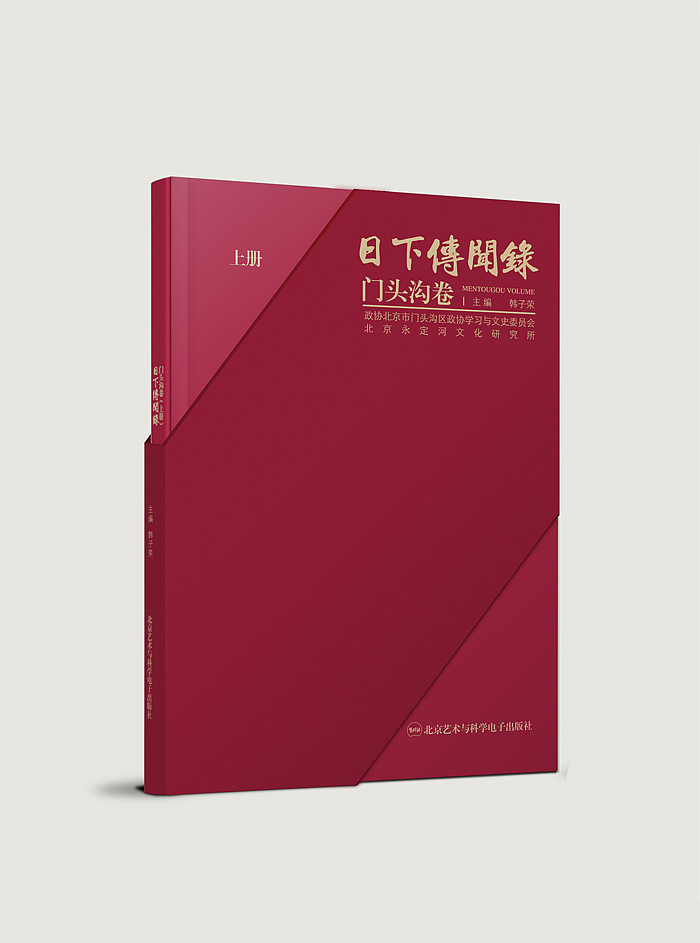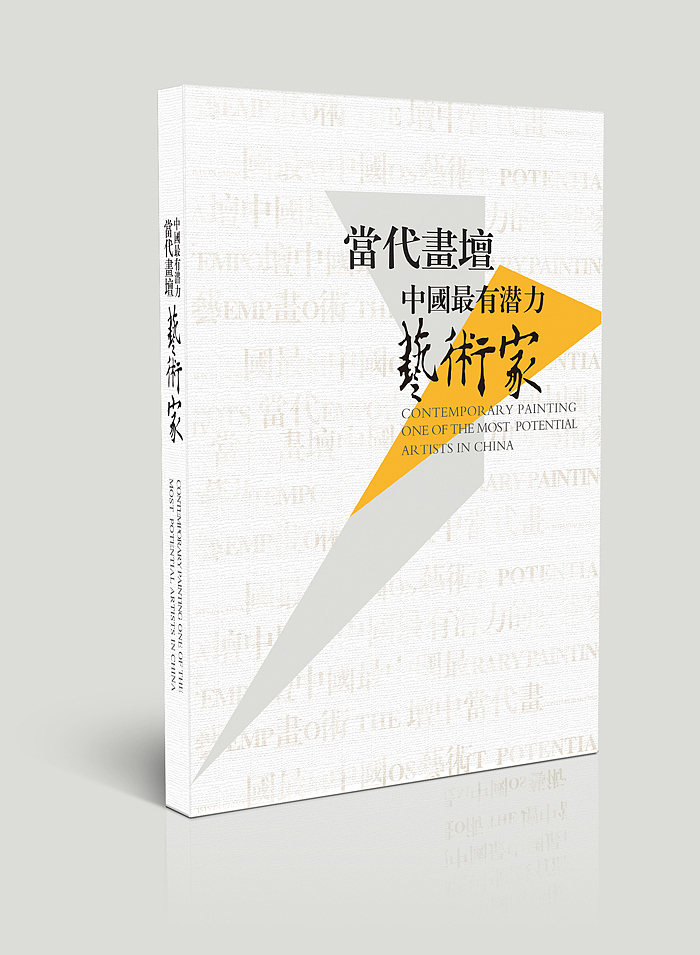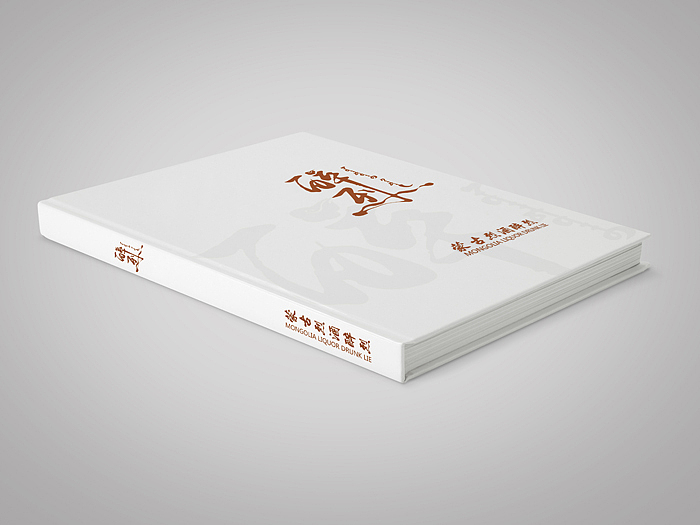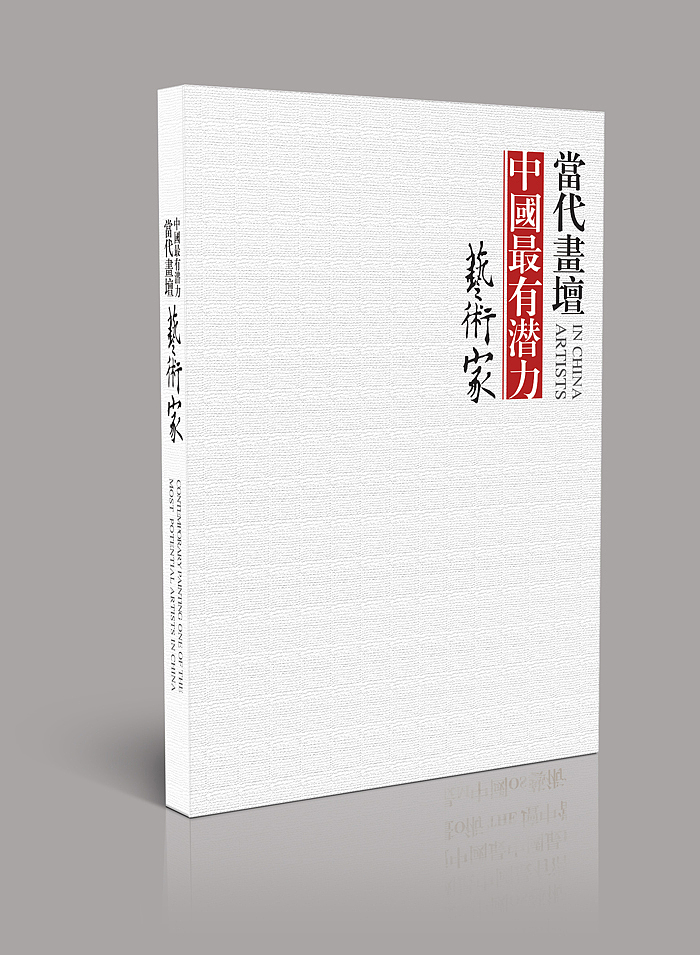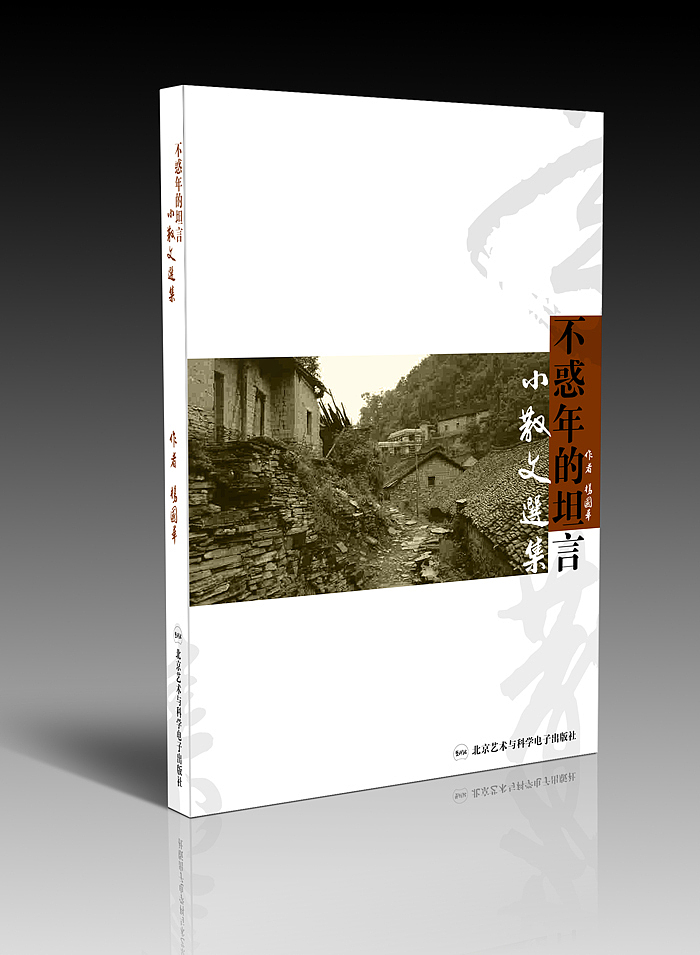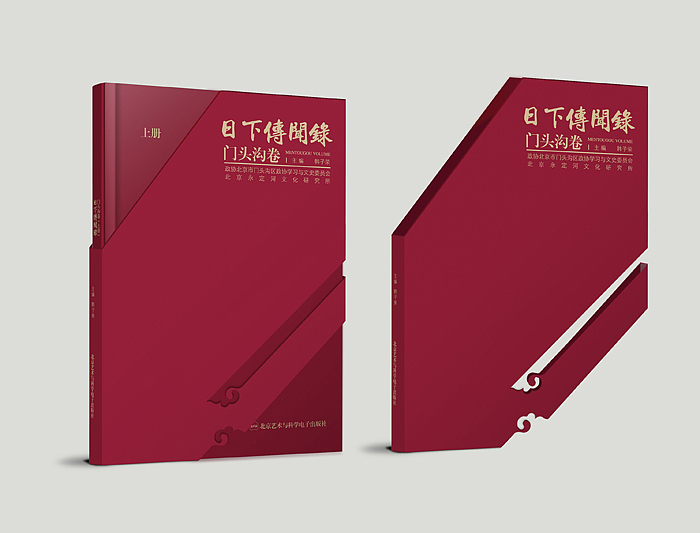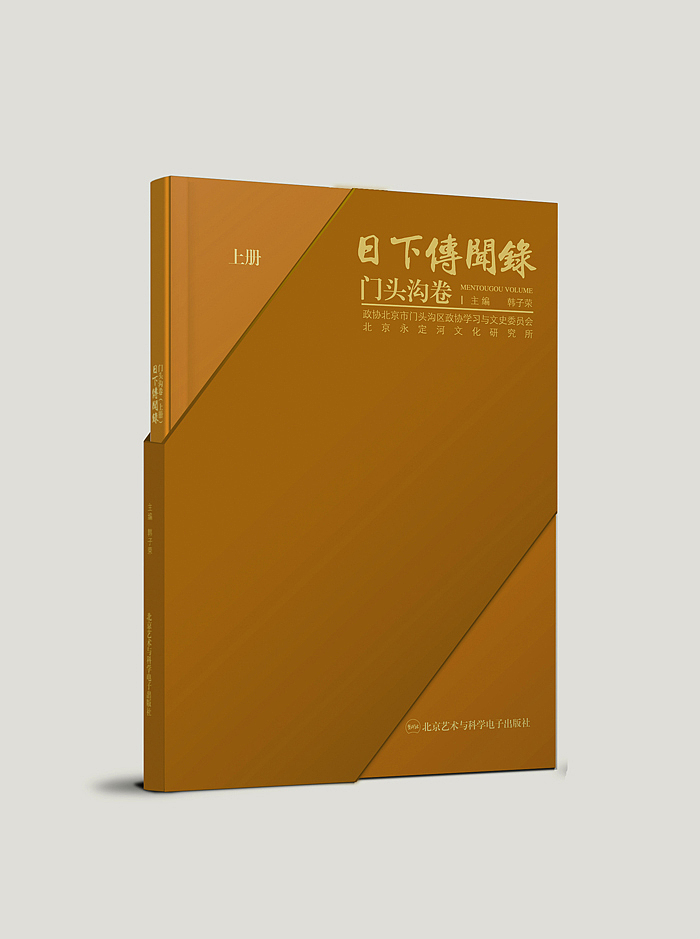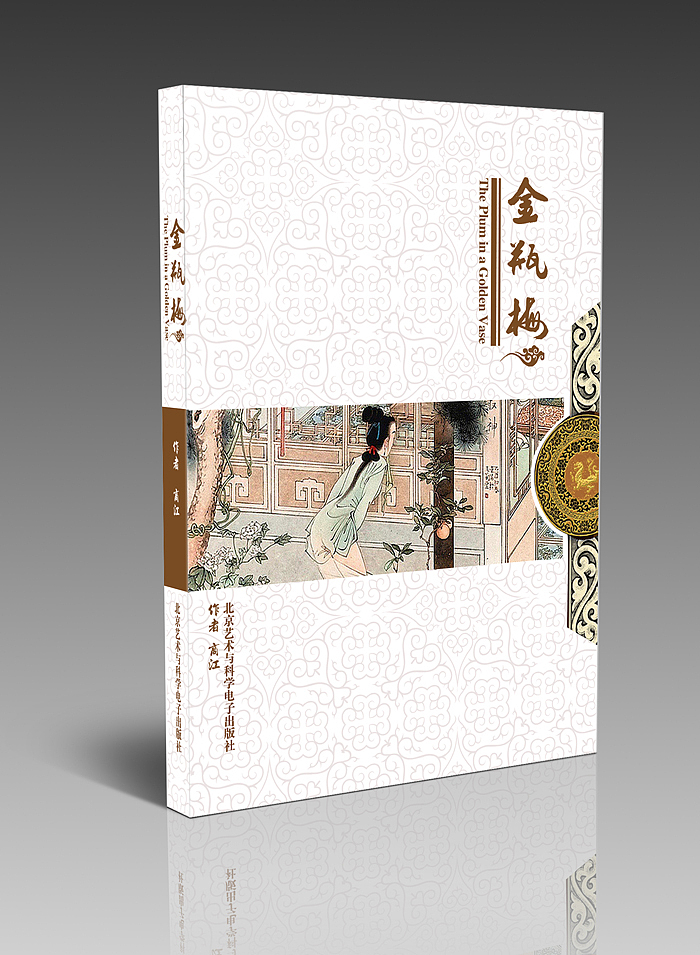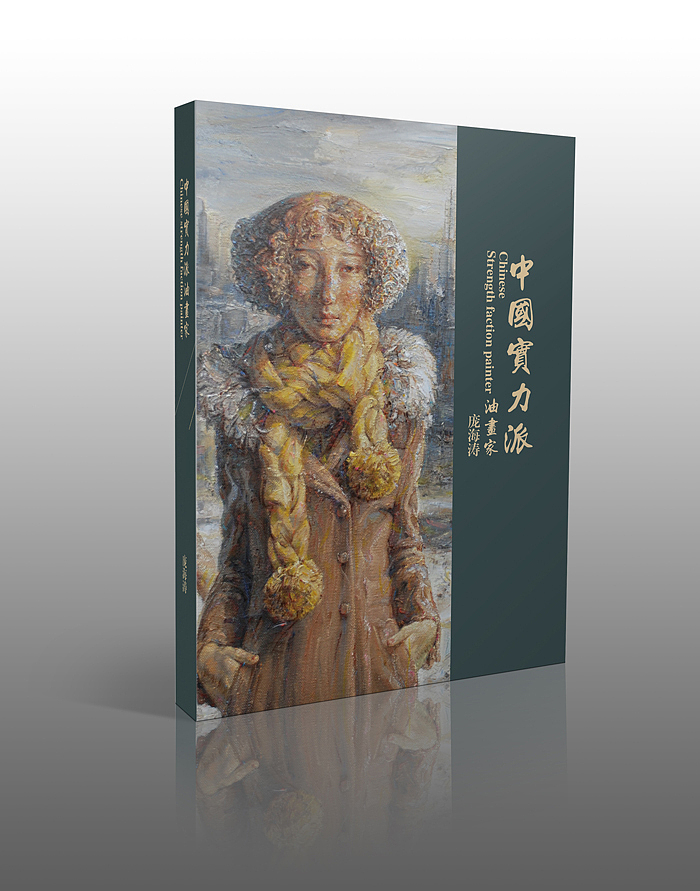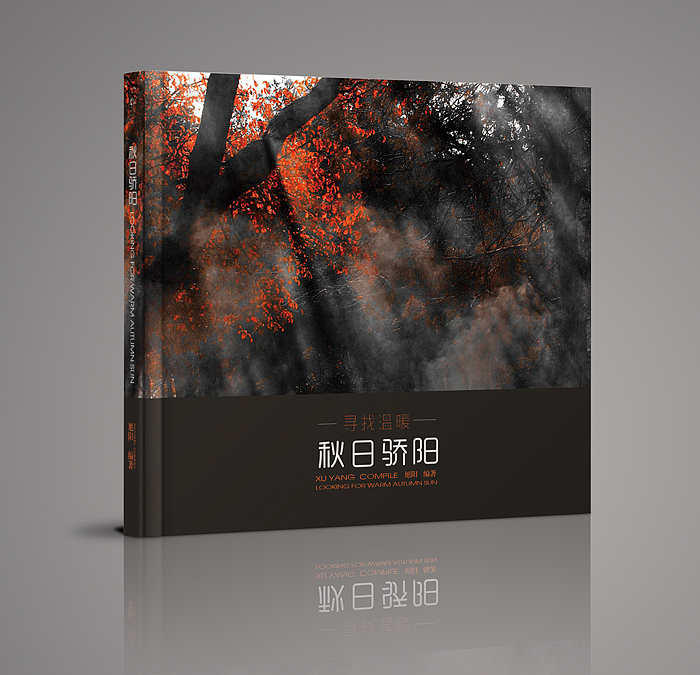
精装书籍封面和字体设计
自己一向喜欢古典的书籍,从小就喜欢写毛笔字书法和钢笔字,随着现代化的冲击,自己的毛笔也丢弃了很多年。但是这些文化类的书籍自己还是很大的感觉和兴趣爱好,对于设计书画类的自己还是很有感觉,这些烫金或者起凸都是模拟色值,所以说精装效果图不能完全的体现出来。
书壳是我的第一个书壳设计,很拙劣,但是我想这也许是我的开端。
表面采用烫金工艺及其加一书壳,这也是我的第一个书壳设计。